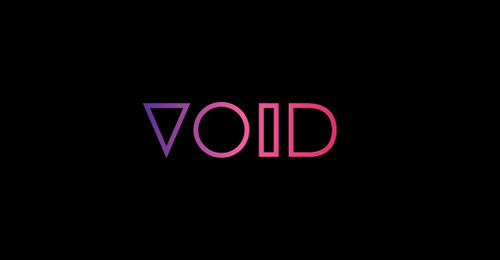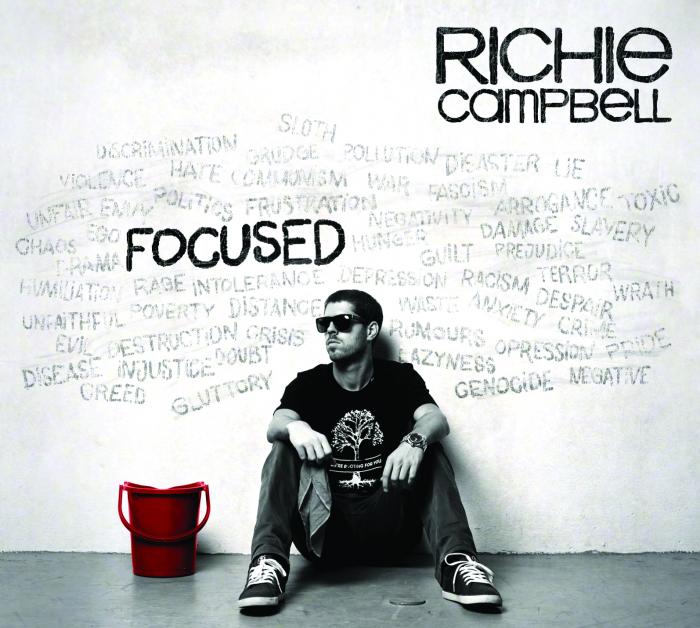
VOID könnte eher konstruiert sein. RICHIE könnte die Kravitz Thermal sein, die unterschiedliche Form der gleichen Buchstaben (E, L) lässt auf eine nachträgliche Verzerrung schließen. Oder sie wurde schlicht und einfach von Hand nachgezeichnet, um das Handgemalte herauszustellen.